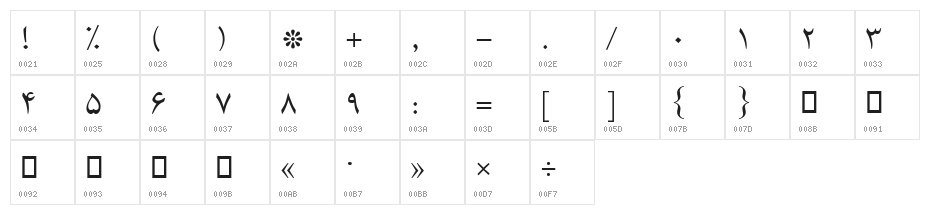
Badr Font
| Caso d'uso | Logos, Invitations, Decorative text |
| Progetti proposti | Ideal for wedding invitations, formal event programs, luxury brand logos, and artistic book covers. |